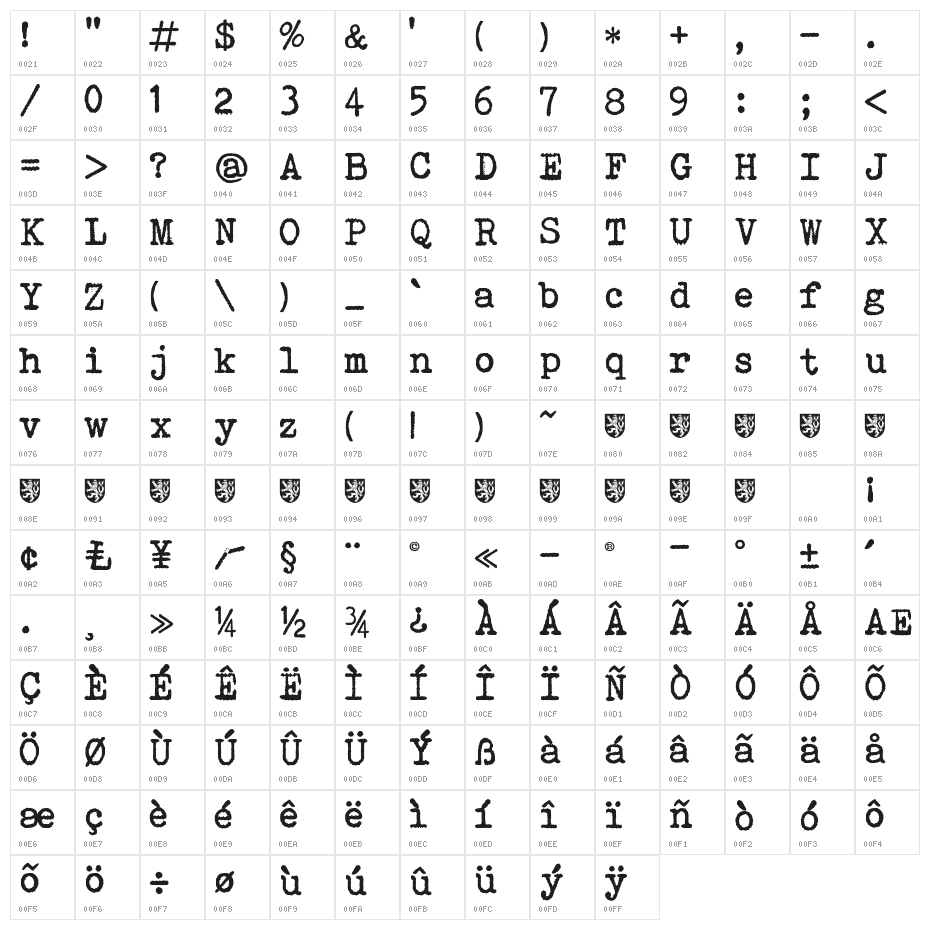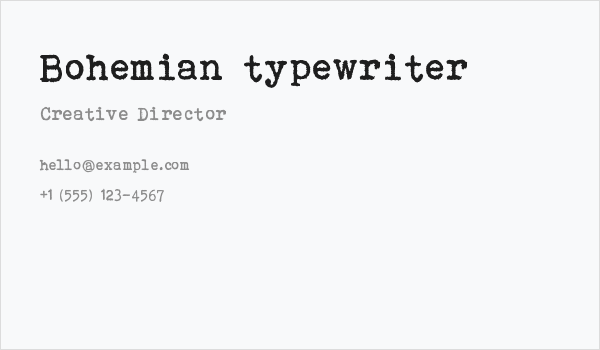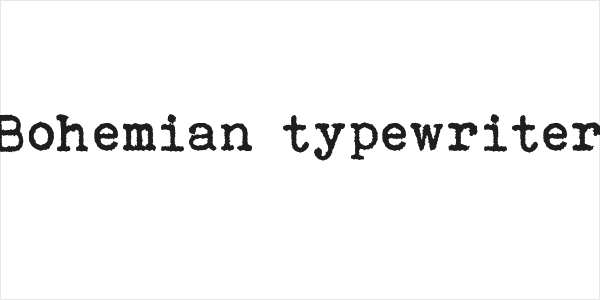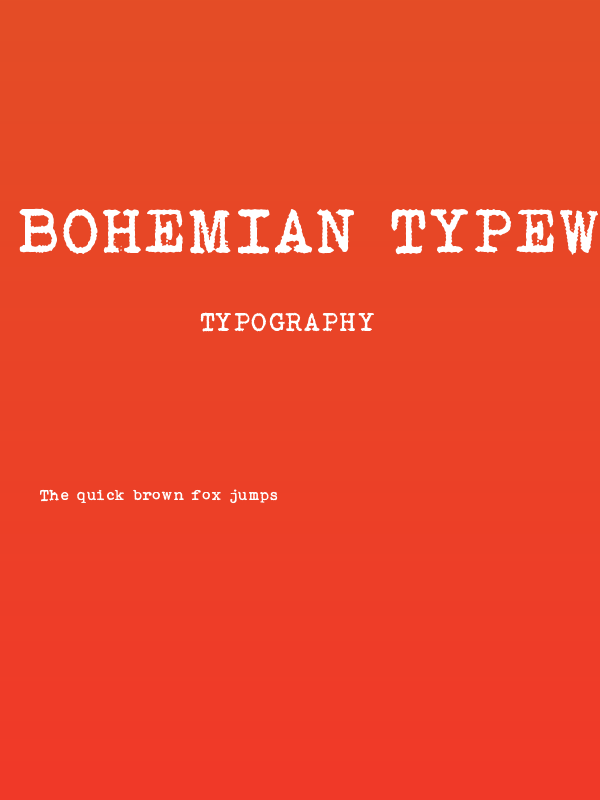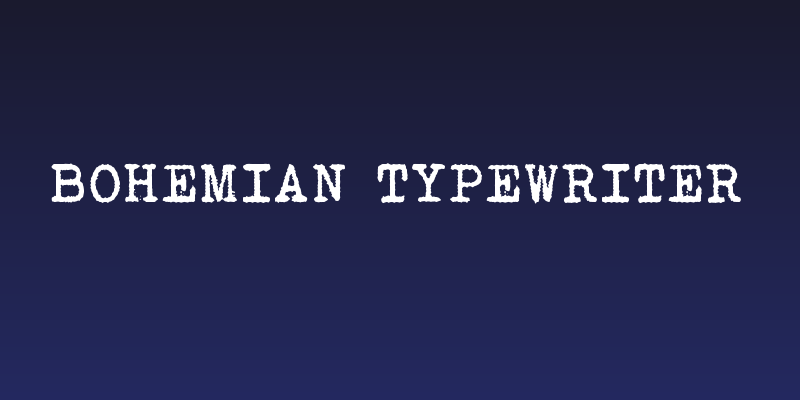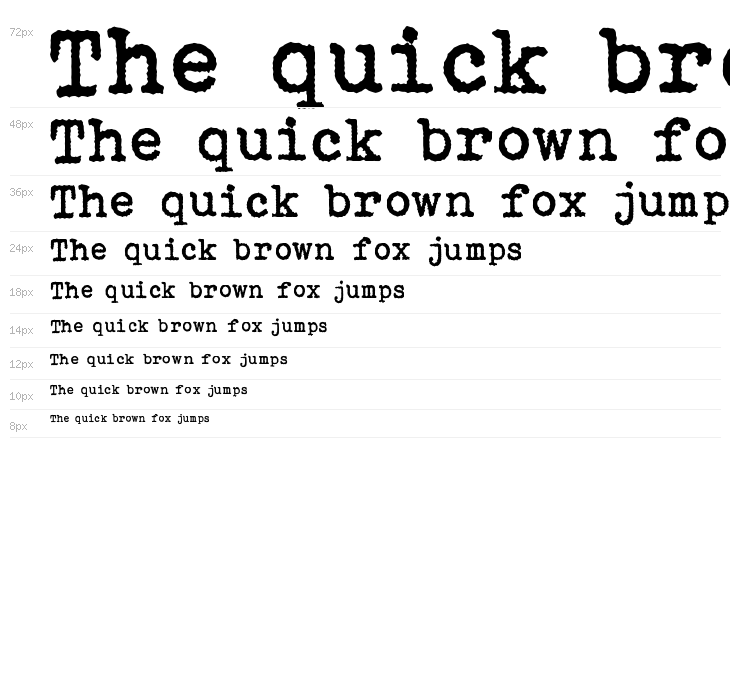
Bohemian typewriter Font
| Gesamtstil | Vintage |
| Anwendungsfall | Headlines, Logos, Decorative text |
| Vorgeschlagene Projekte | Ideal for retro-themed designs, typewriter art, vintage posters, and historical documents. |